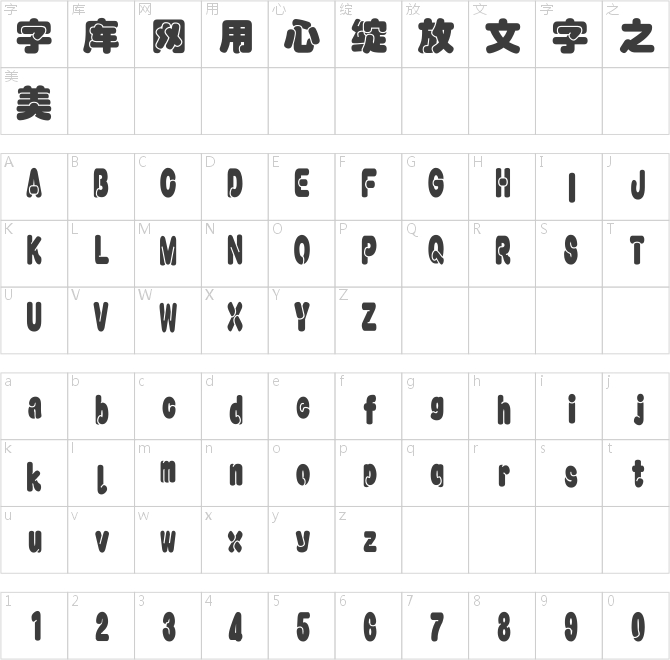
字体名称: ?文鼎琥珀简繁
?文鼎琥珀简繁
文鼎琥珀的简体和繁体big5合并形成的,二次修订时补全了原big5的汉字,兼容新版win10
更新Power TrueType Version 5.0版,和原Power TrueType Version 4.0或Power TrueType Version 4.5版本相比又将原Power TrueType big5的扩展471个外字集的部分没有映射字码点的汉字进行了对号入座,并修复『?』字误映射到『抝』字位置的错误。
20220120更新Power TrueType Version 5.5版:添加日语当用汉字。一共16721个汉字。
20220204更新:修正「爲」「僞」分别显示为「為」「偽」的错误。